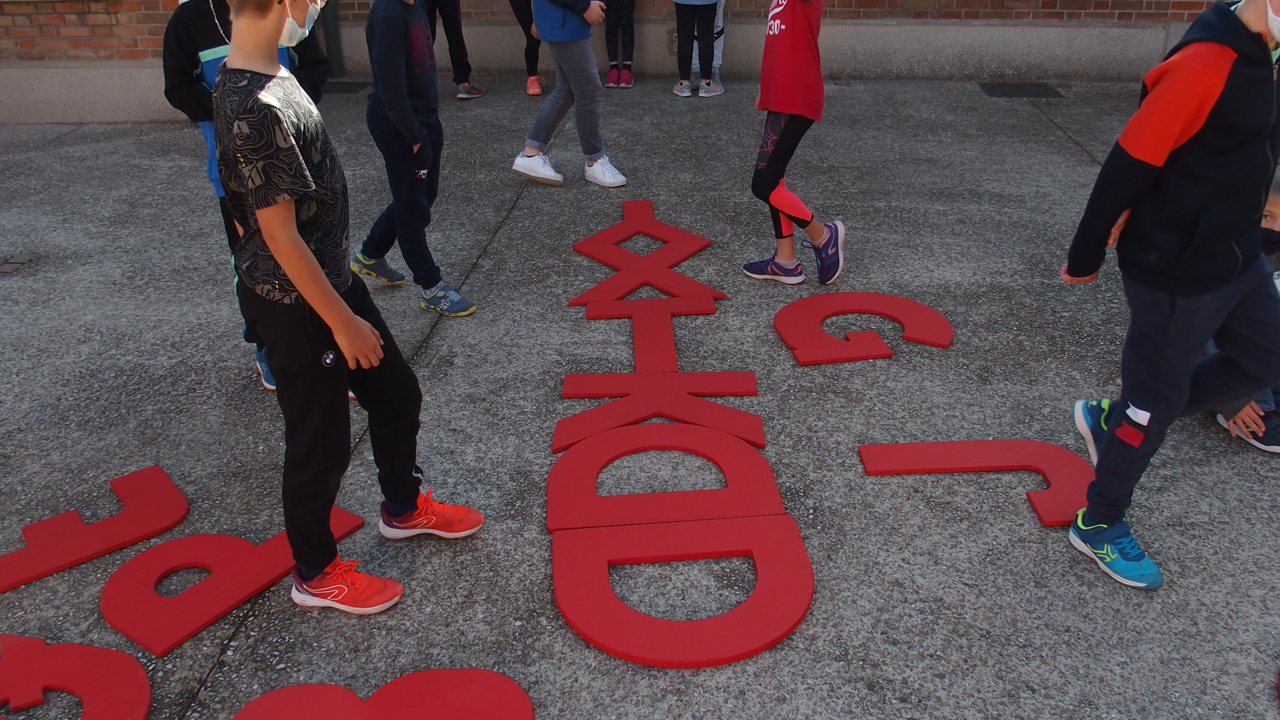
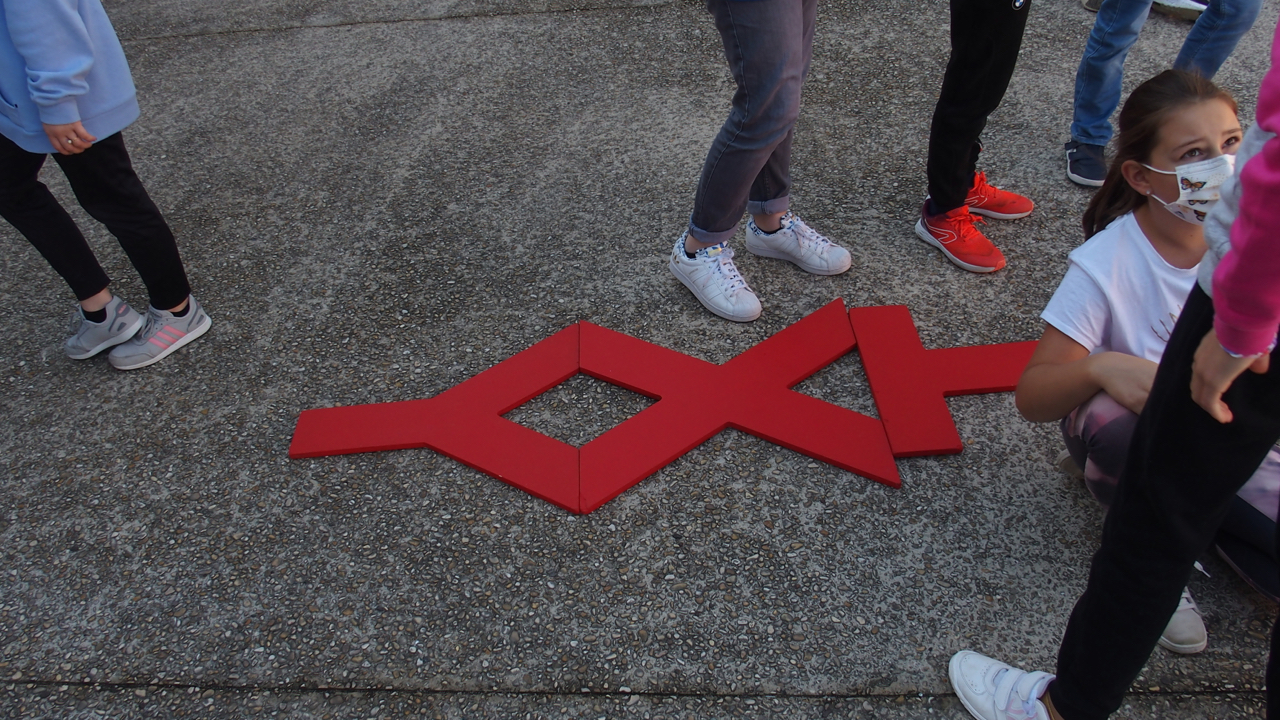
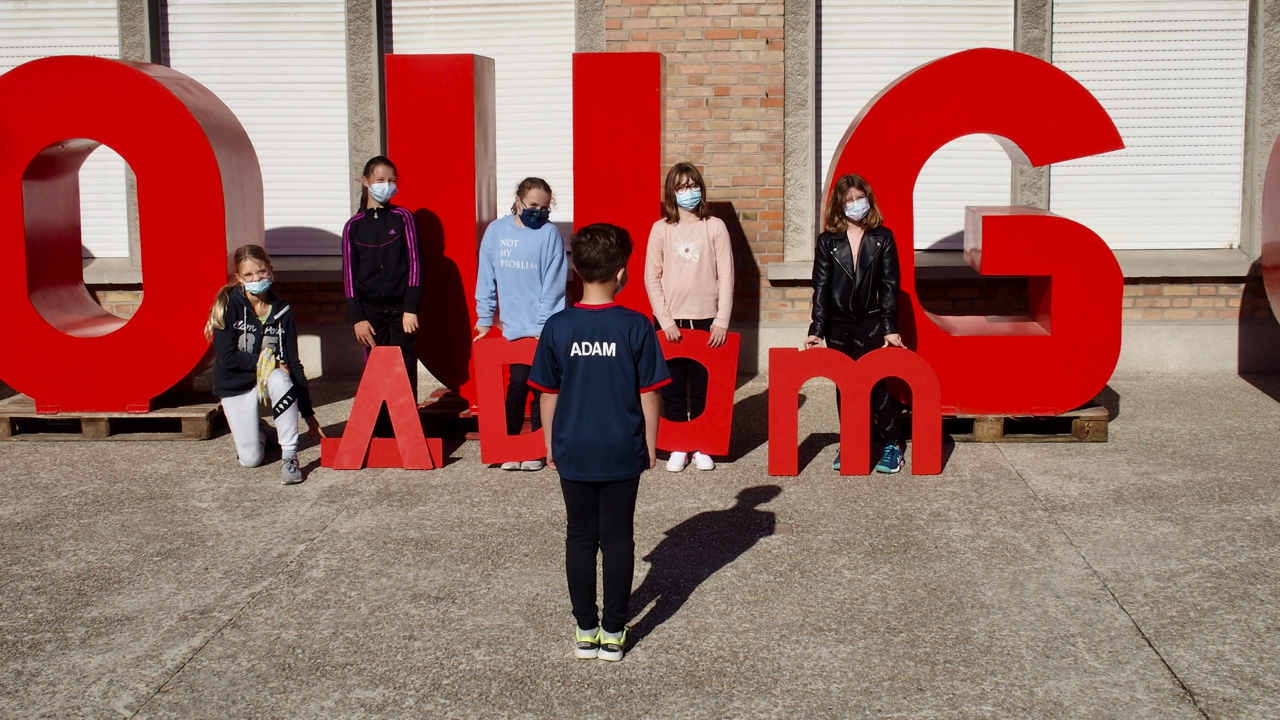
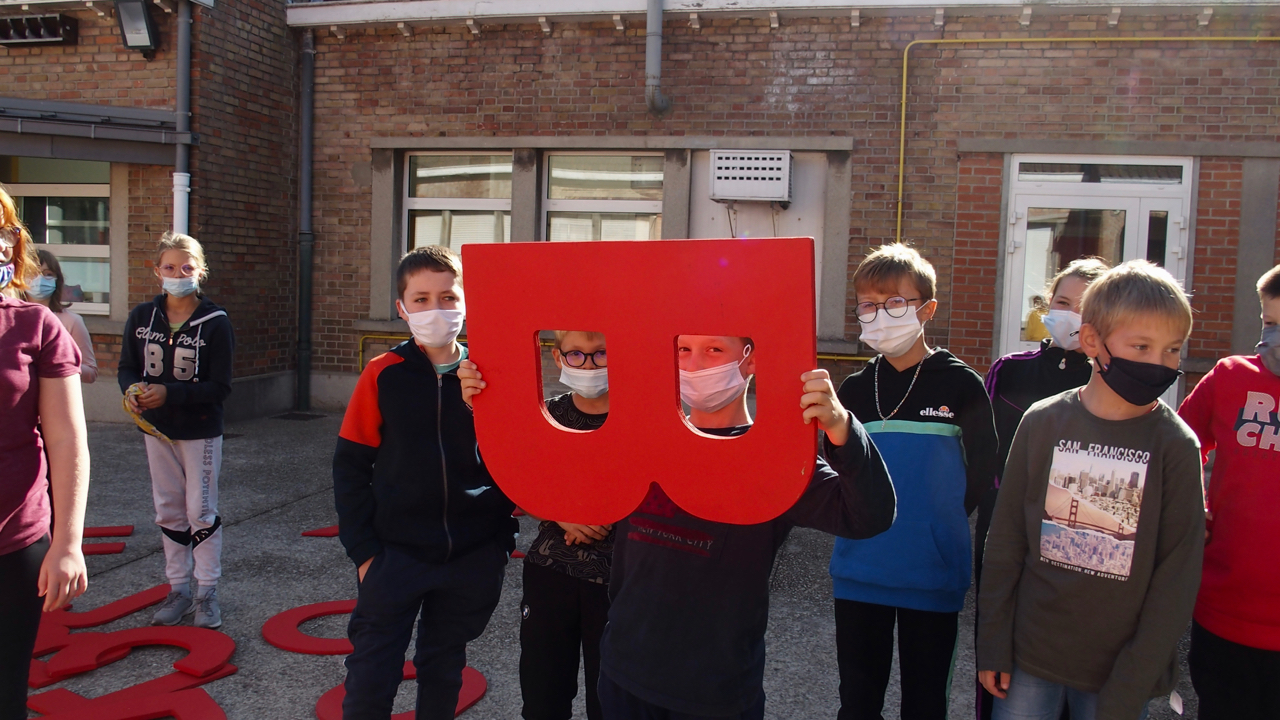
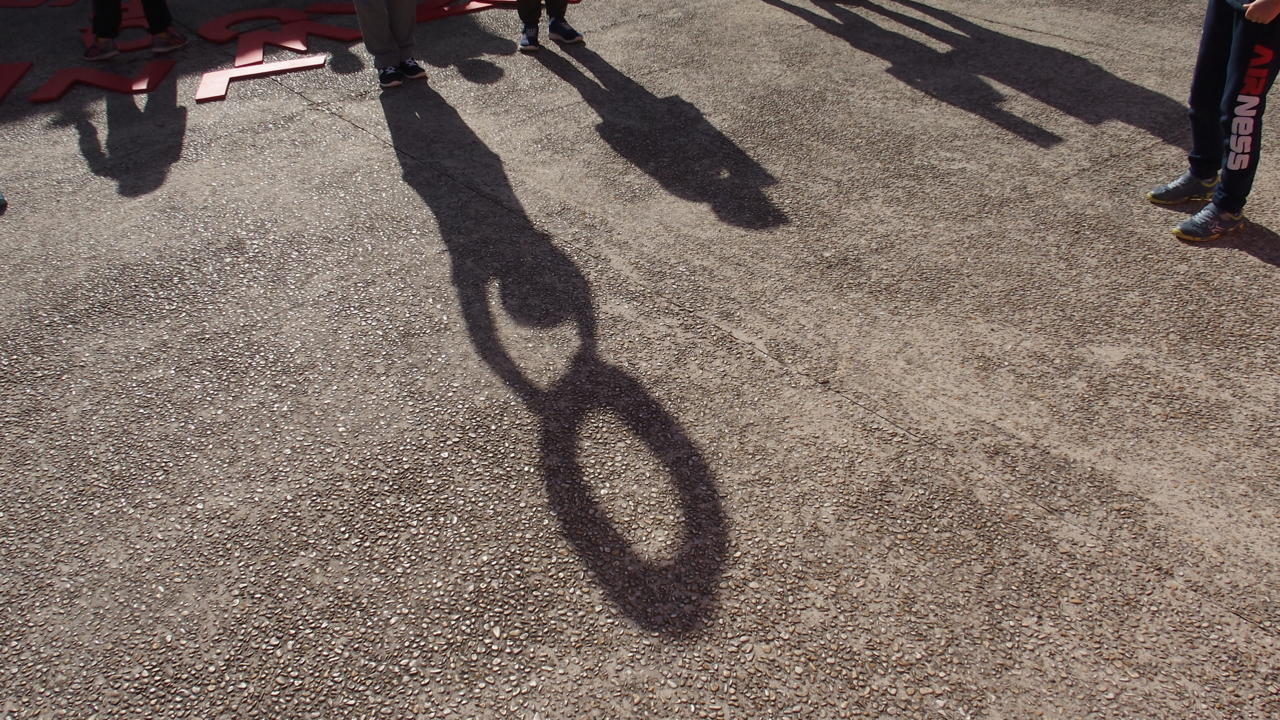
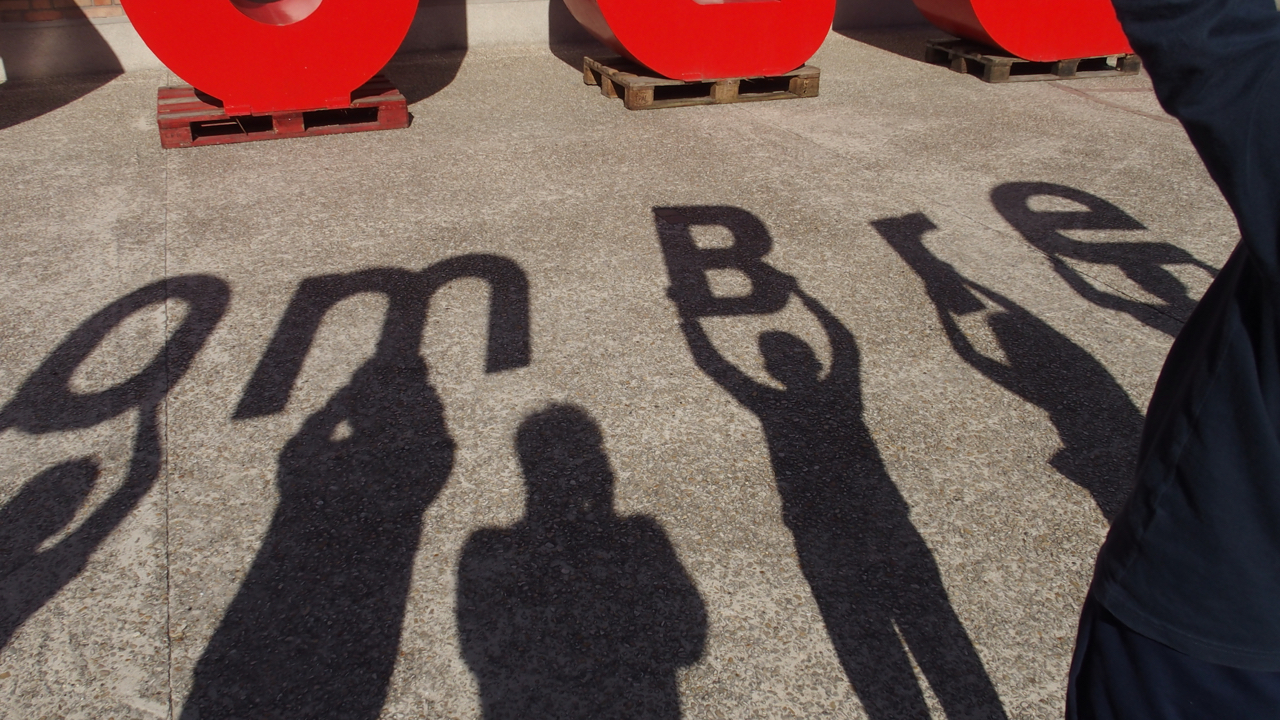
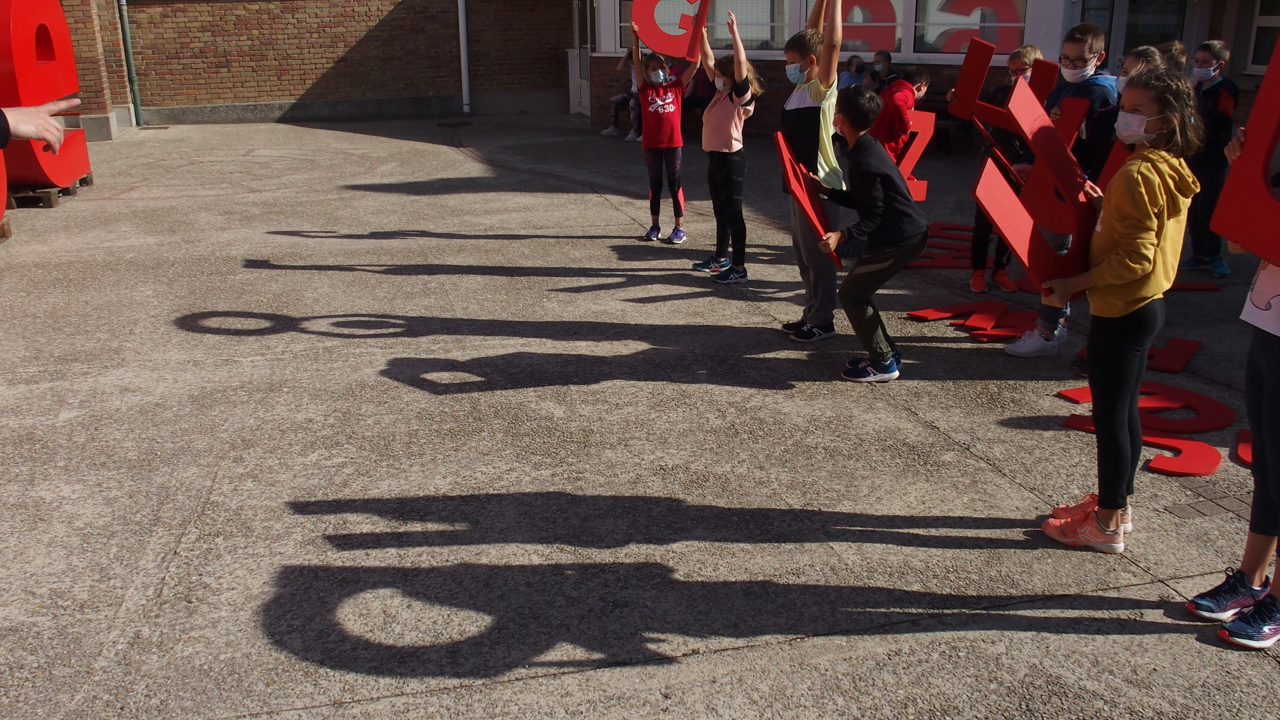
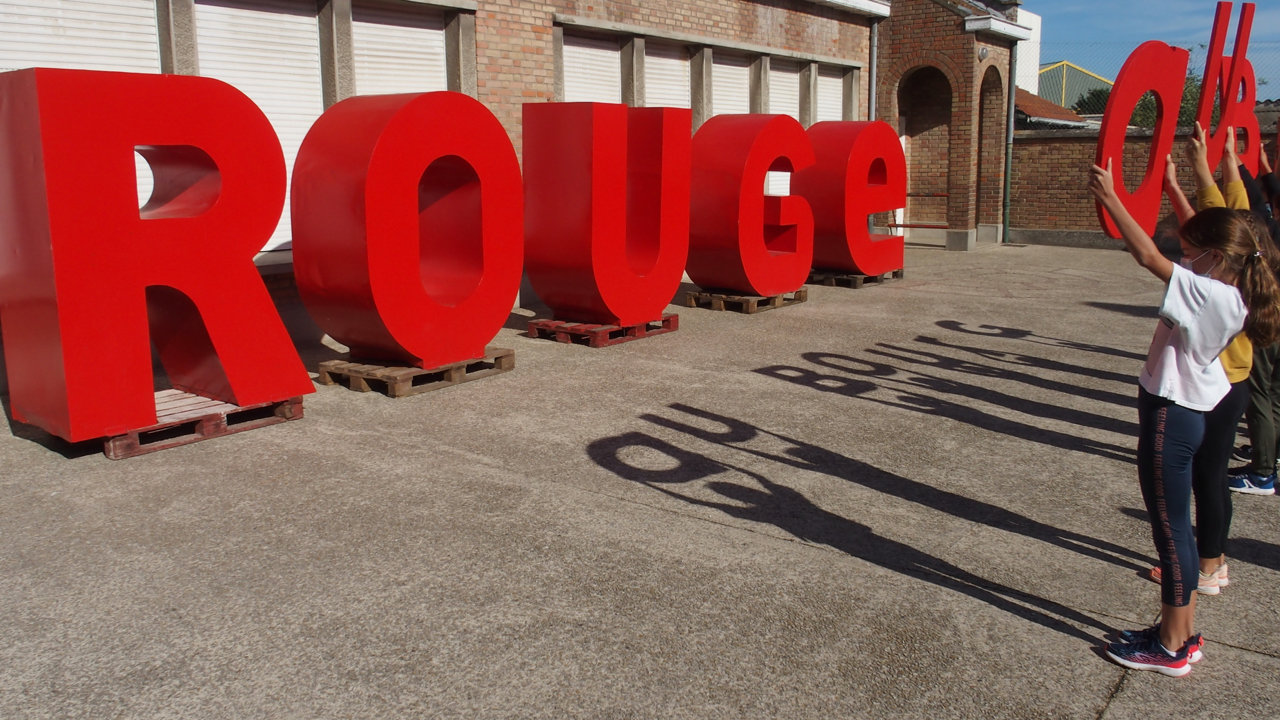
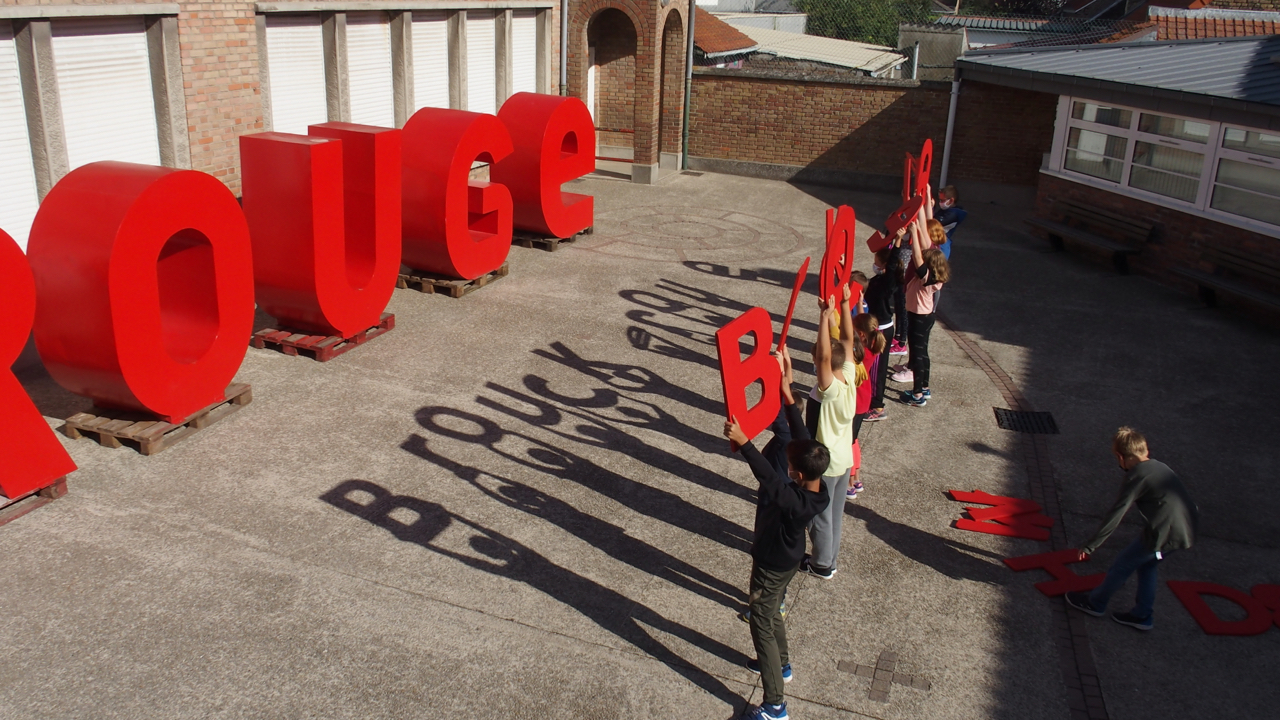
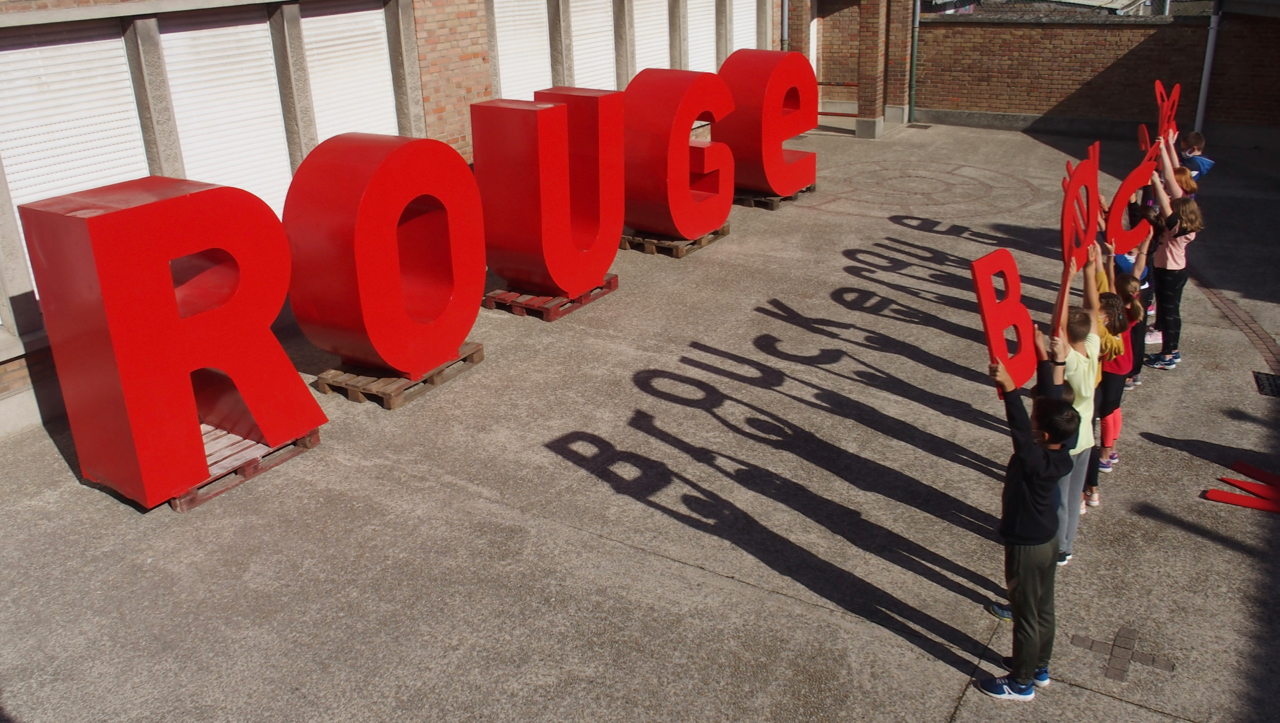
Aucune recette vraiment.
Présence commune.
J’amène ma pratique.
Pratique pour moi.
Juste se rencontrer, parler, et agir.
Composer un geste,
artistique, ensemble.
Voila, en images,
quelques traces,
de la chanson.
De gestes.
Des fois des choses se passent.
Plus que d’autres, fois.
Les laisser agir, s’emparer du dispositif,
et moi devenir photographe
de l’autonomie créatrice en action.
Des fois pointer. Cadrer, une image.
Avouer que, dans ces instants, je me sens proche d’un photographe de guerre cherchant à capter le fugace.
Fugace se tenant souvent plus dans le chaos que dans la pose.
Je pense souvent à Gilles Caron, disparu au Cambodge.
La pose, on y échappe pas. Avec les prénoms.
Et les copains, copines sur la photo.
Tout le monde s’aide pour inscrire son prénom.
Les lettres de l’un servent pour l’autre.
Et ça tourne!
Moteur.
Des fois j’en garde une.
Là, Adam.
Redondant.
Dans son dos, inscrit aussi.
( vous ai-je dit qu’un pan de ce projet est sous le signe de la pomme, de l’arbre de la connaissance, Eve et cie ? )
Ce jour-là, le soleil s’invite. Très vite, le jeu des ombres se met en place.
Regardez justement, là, après « OMBRE », ce petit moment de chaos…
Et justement celui qui le tient, haut, le « o ».
Là, il se passe quelque chose, de capté.
Lui aussi, je crois, l’a vue,
la jolie forme ombrée composée.
Lettre, tête et bras.
Ce jour-là, l’ombre nous a porté. L’atelier augmenté. On a beaucoup joué avec. Composer des agencements lettristes. À la récré, je suis retombé sur mon tableau, pas effacé. Trace aussi des échanges. Trace infime.